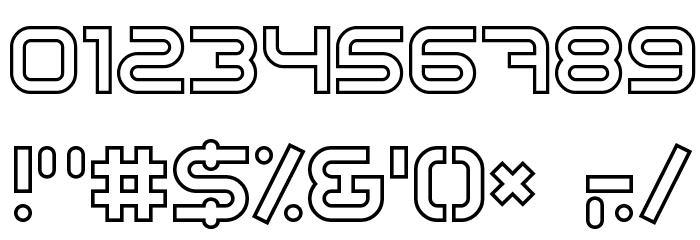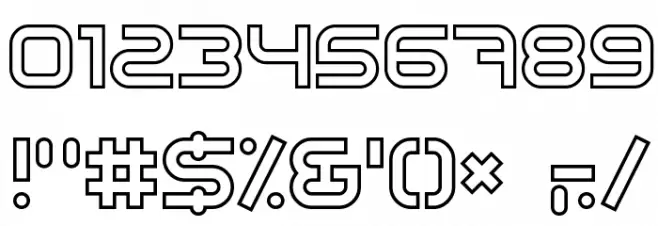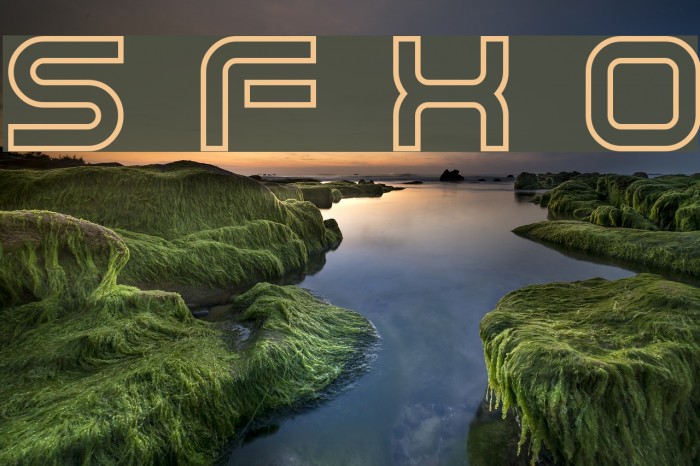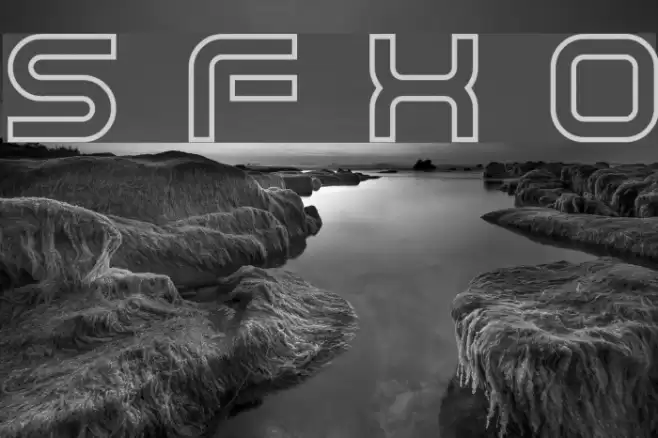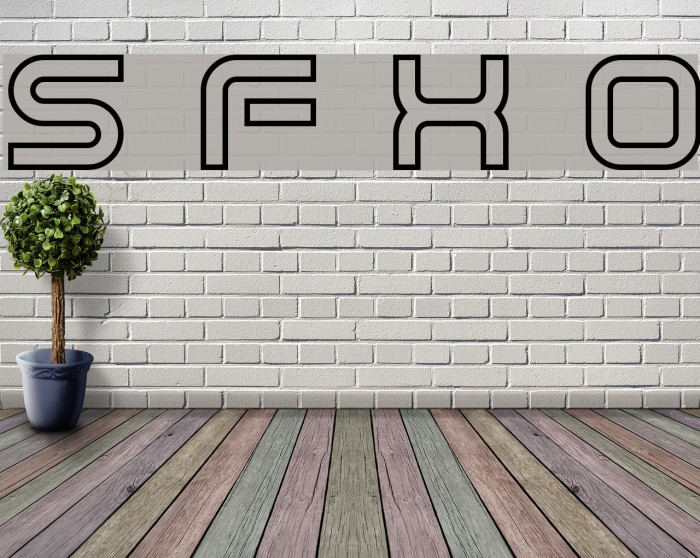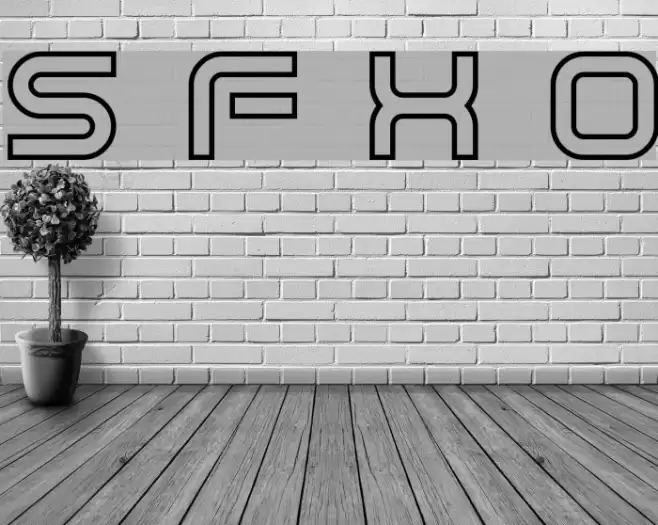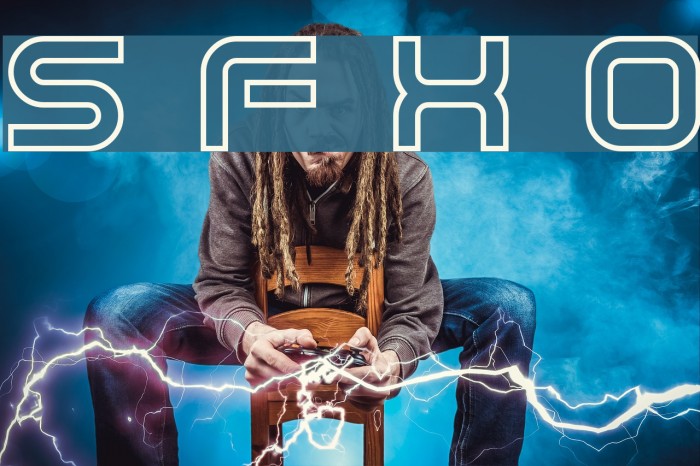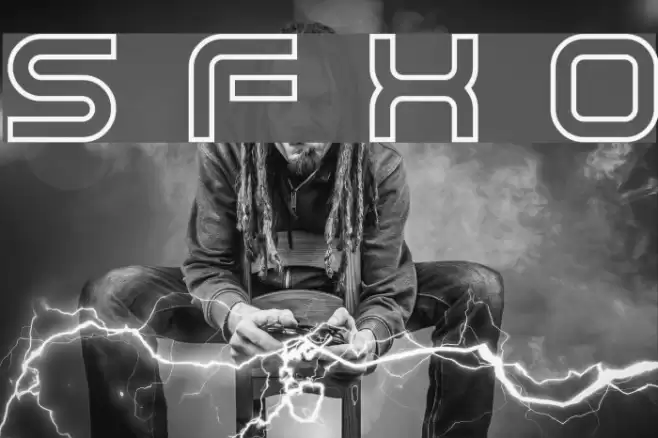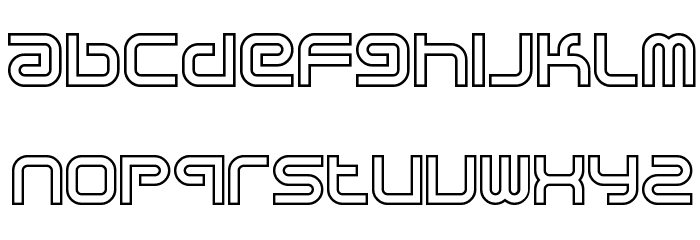
Sci Fied X Outline Font
✎ Futuristic
| Рекомендуемые проекты | Ideal for sci-fi themed projects, tech branding, video game titles, and futuristic posters. |